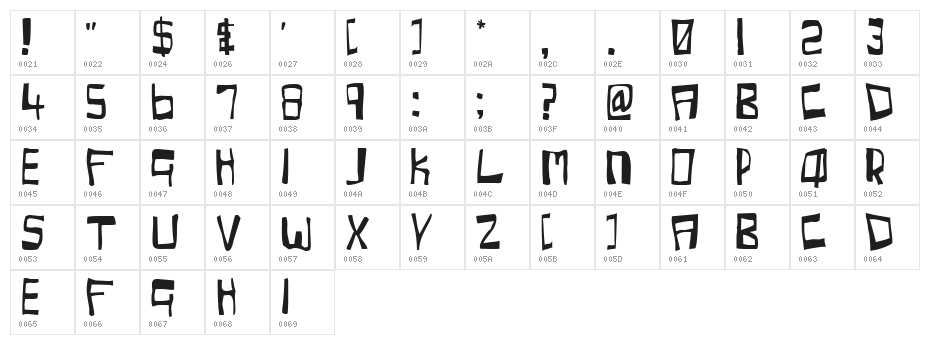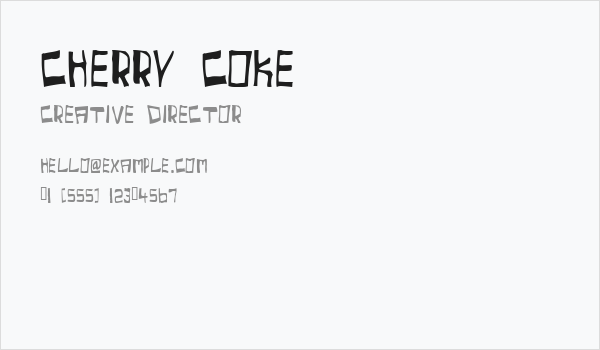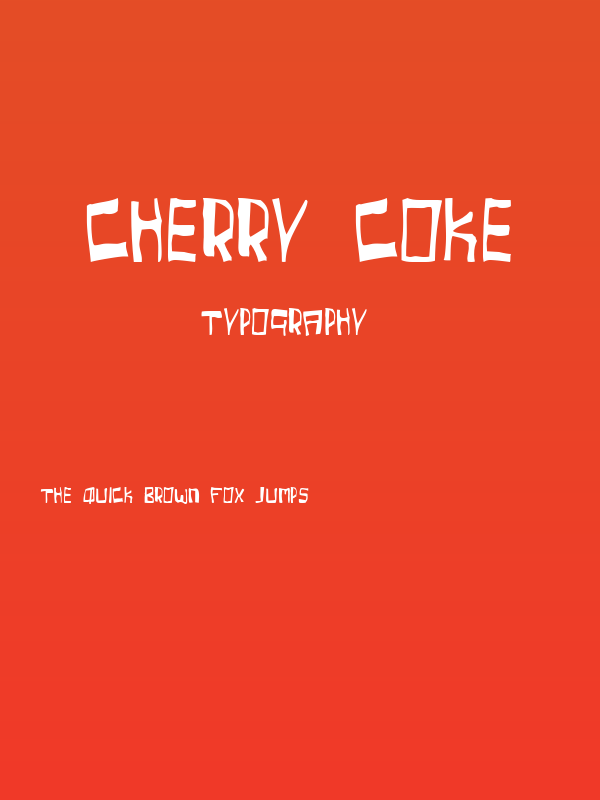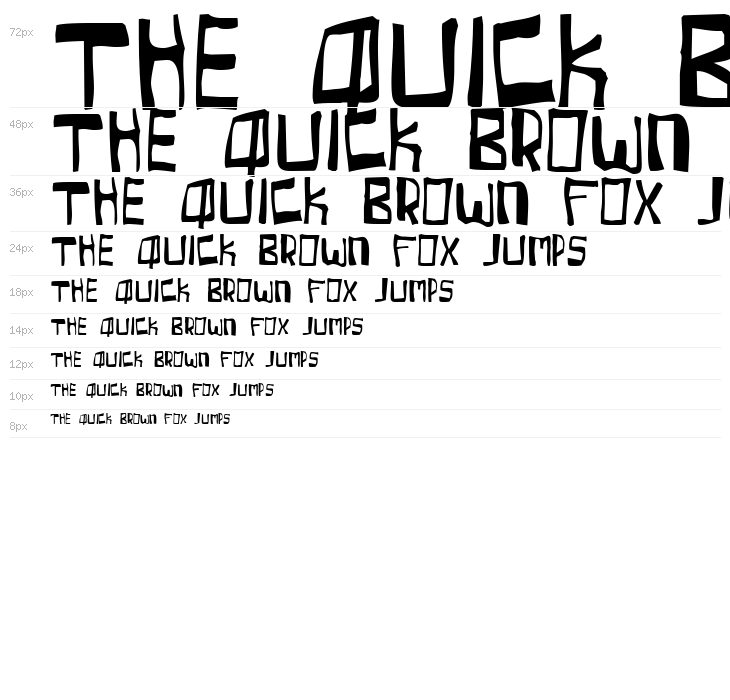
Cherry Coke Font
| Stile generale | Playful, Artistic, Modern |
| Progetti proposti | Ideal for creative projects such as posters, album covers, children's books, and branding for playful or artistic products. |